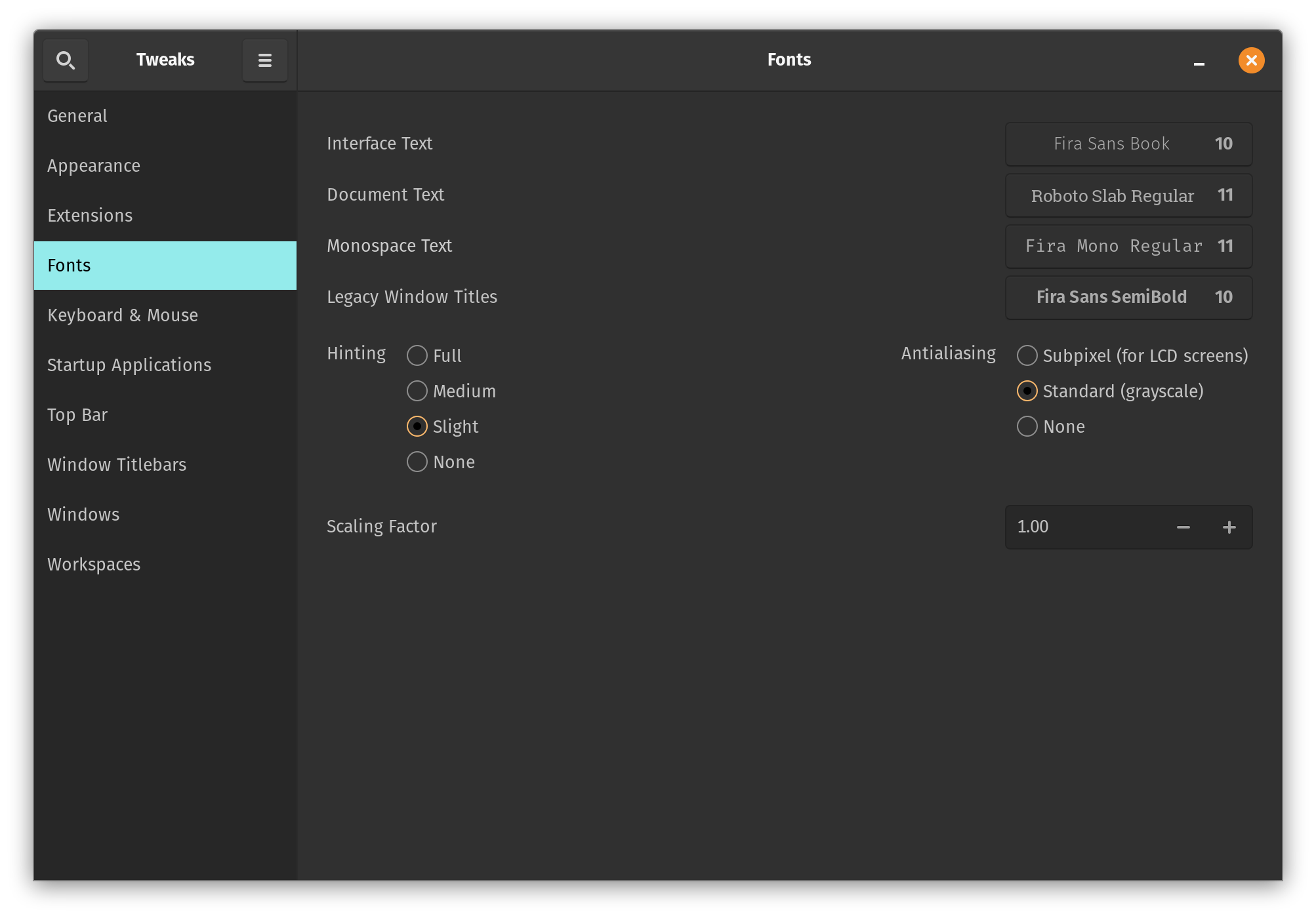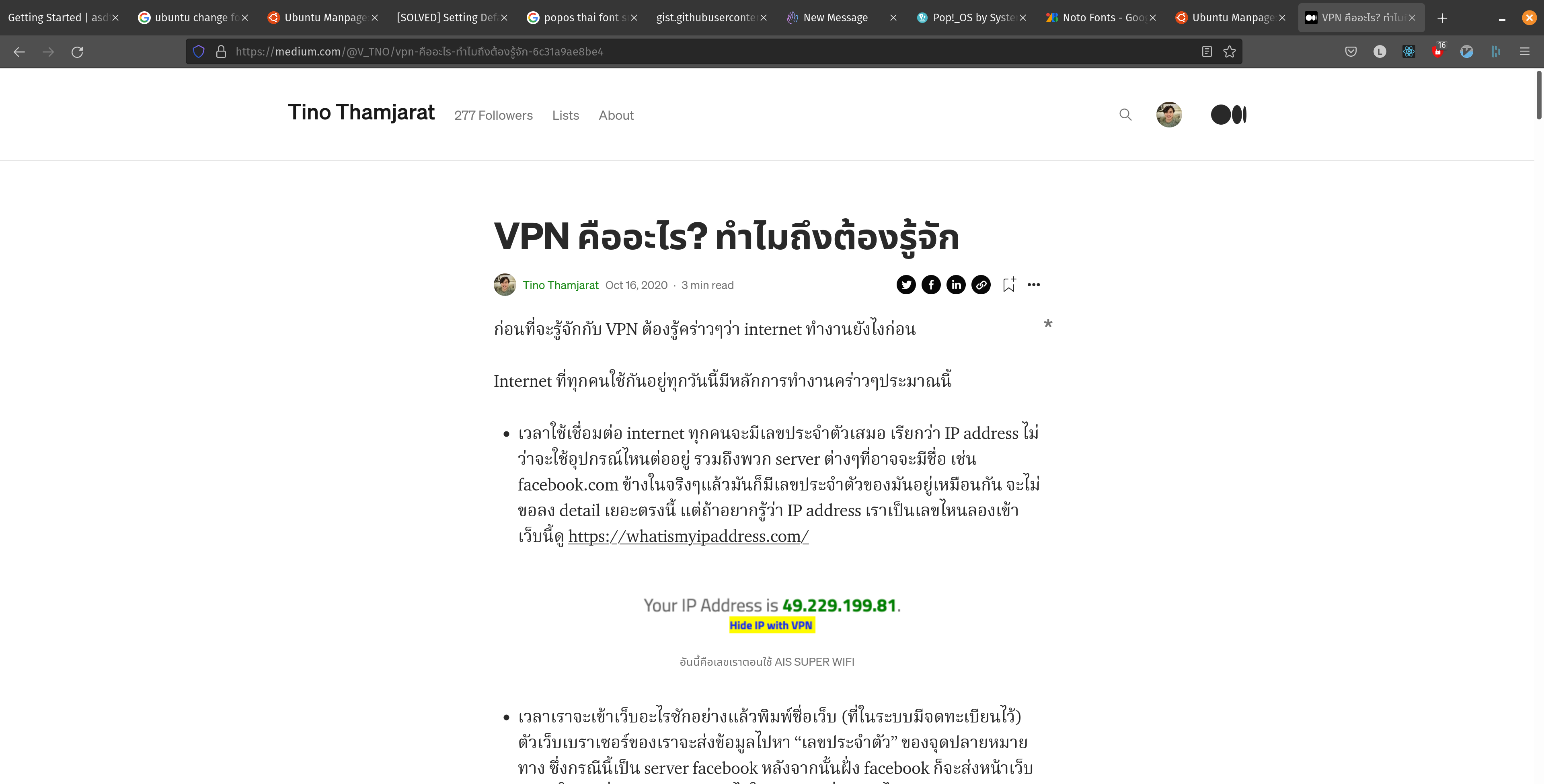
สิ่งที่น่าหงุดหงิดอย่างเดียวก็คือ default font ของภาษาไทยมันสุดจะน่าเกลียด ไม่แน่ใจว่าเป็น font อะไรแต่มันน่าเกลียดเอามาก ๆ ซึ่งการเปลี่ยน font สำหรับภาษาแต่ละภาษาเป็นเรื่องนึงที่ไม่ค่อยตรงไปตรงมาเท่าไหร่ใน PopOS โดยมีสองวิธีหลัก ๆ ที่สามารถทำได้
1. เปลี่ยน system font ไปเลย
วิธีแรกคือการเปลี่ยน font ของทั้งระบบไปใช้ font ที่รองรับภาษาไทยไปเลย สำหรับท่านี้จะง่ายหน่อยเพราะสามารถใช้ GUI appจัดการได้
หลังจากนั้นก็เปิดโปรแกรมขึ้นมา จะเห็นว่ามันมี tab Fonts อยู่ซึ่งเราก็สามารถเลือกใช้ font ต่างกันในแต่ละจุดได้ เช่น ใน document อยากให้เป็น font มีหัว แต่อยากให้บน interface เป็น font ไม่มีหัวอะไรแบบนี้
2. เปลี่ยนแค่สำหรับภาษาไทยเท่านั้น
วิธีนี้สำหรับคนที่ชอบ font ภาษาอังกฤษที่ตั้งค่าไว้แล้วอย่างผม คือ เราจะเปลี่ยนแค่สำหรับภาษาไทยเท่านั้น วิธีนี้จะใช้สิ่งที่เรียกว่า font config ซึ่งเป็นท่าที่ไม่มี GUI ต้องใช้ terminal อย่างเดียวเท่านั้น
โดยหลังจากเช็คแล้วว่า font ถูกอ่านอย่างถูกต้อง ลองเปิดภาษาไทยบนเว็บหรือเขียนภาษาไทยในแอพต่าง ๆ จะเห็นว่า font จะเปลี่ยนเป็นตัวที่เราตั้งค่าไว้ และ font ภาษาอังกฤษยังเป็นตัวเดิม